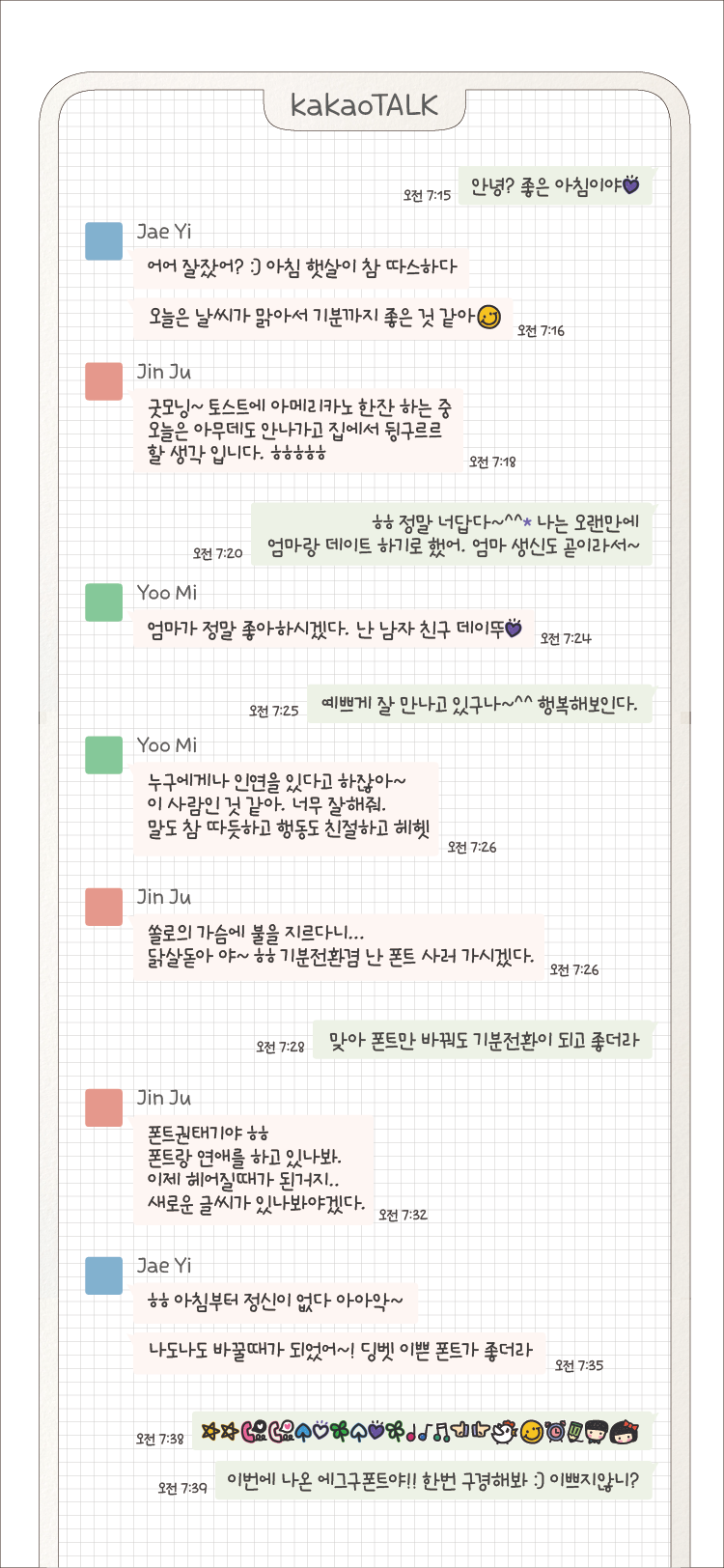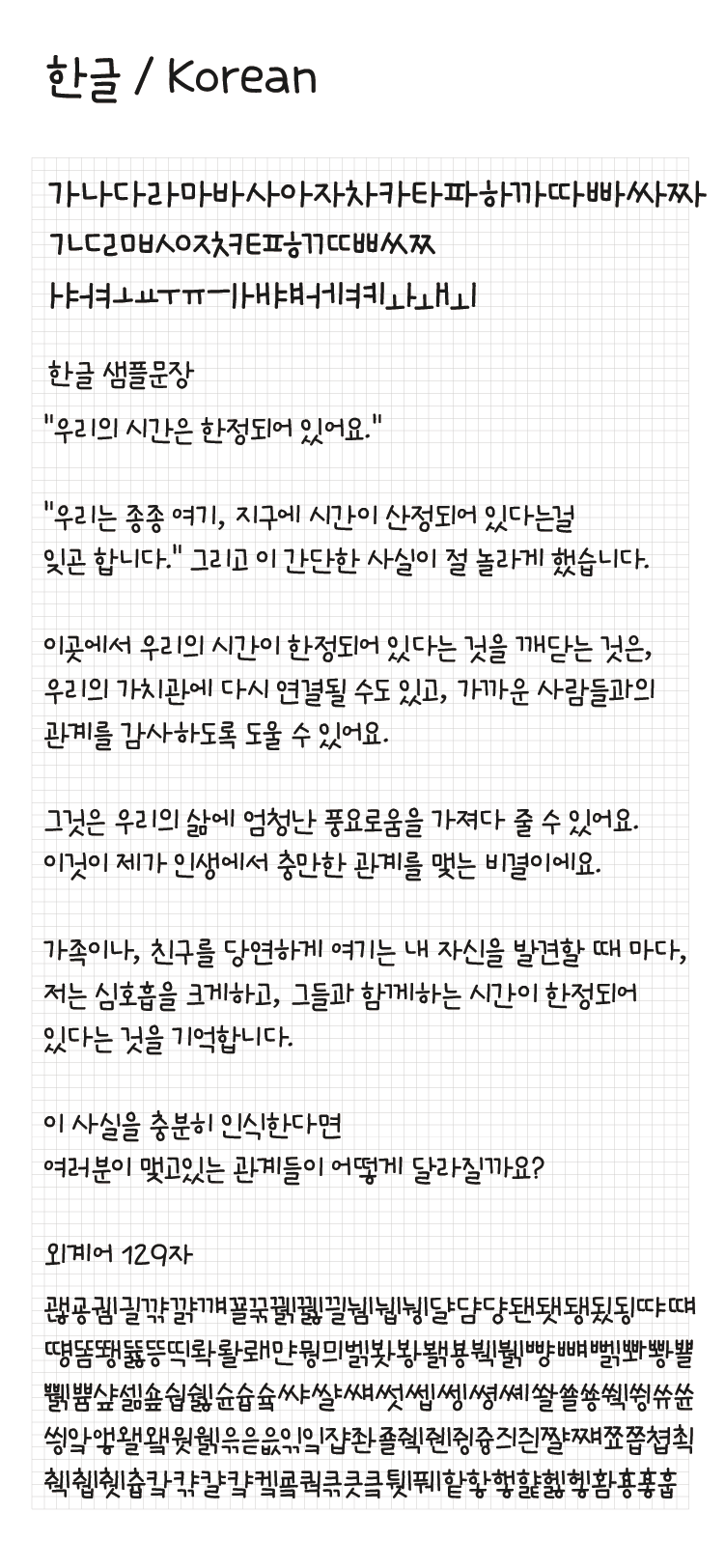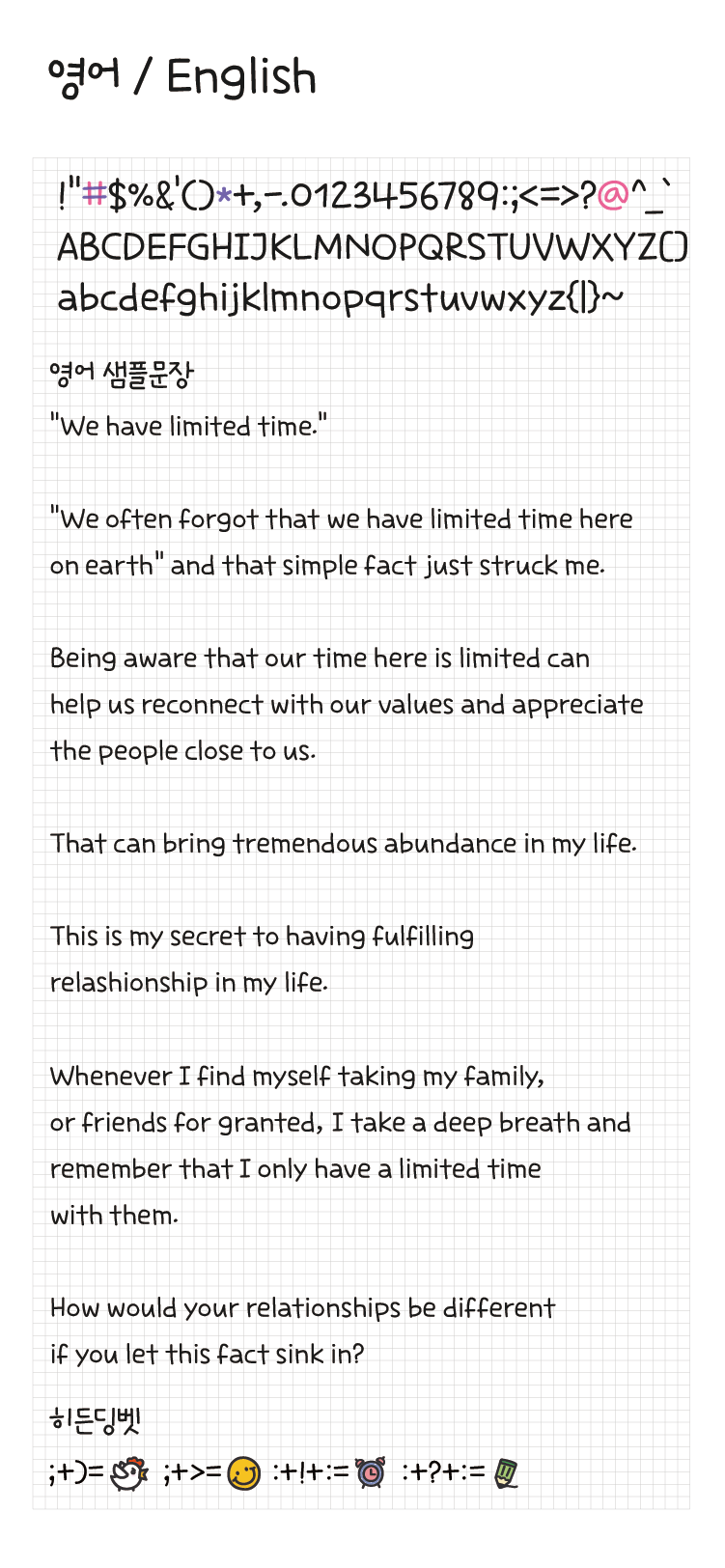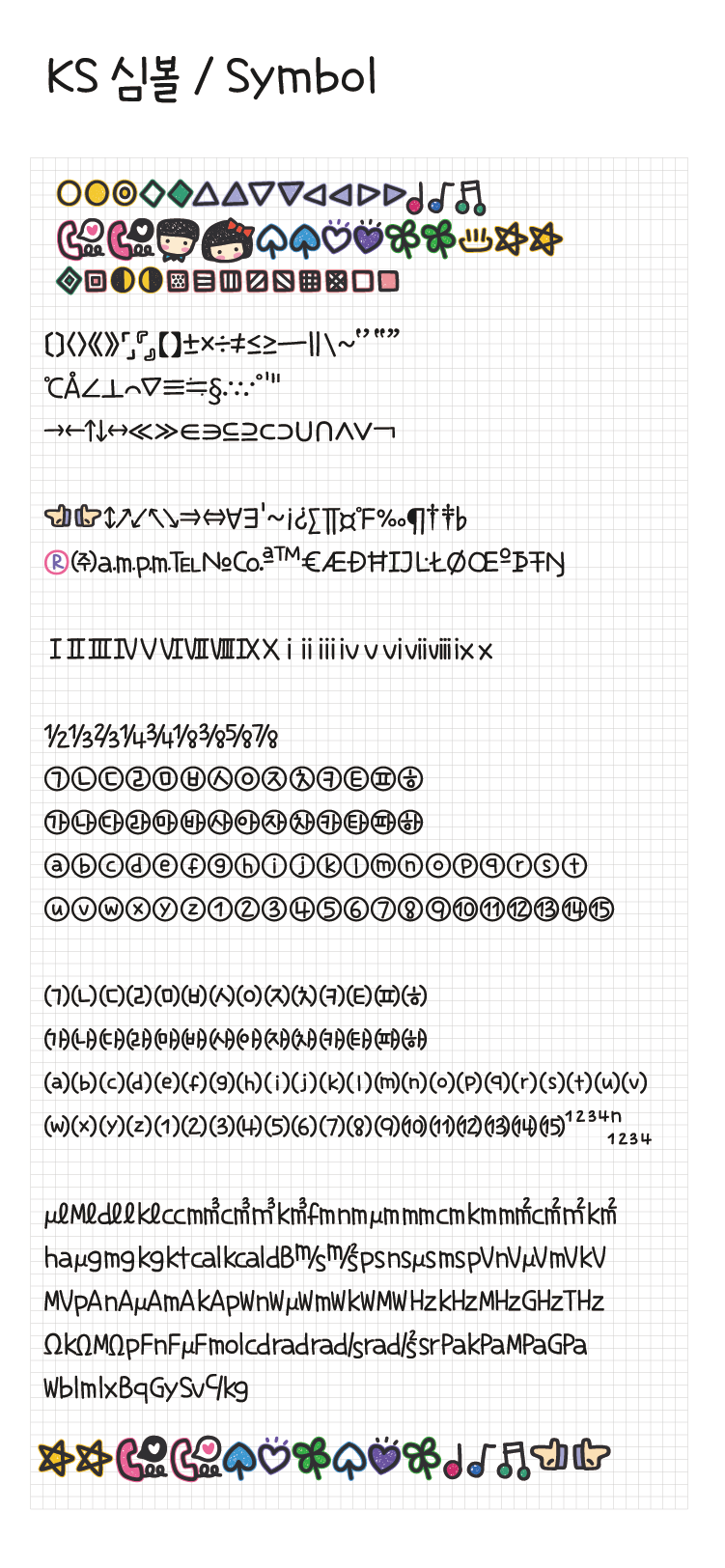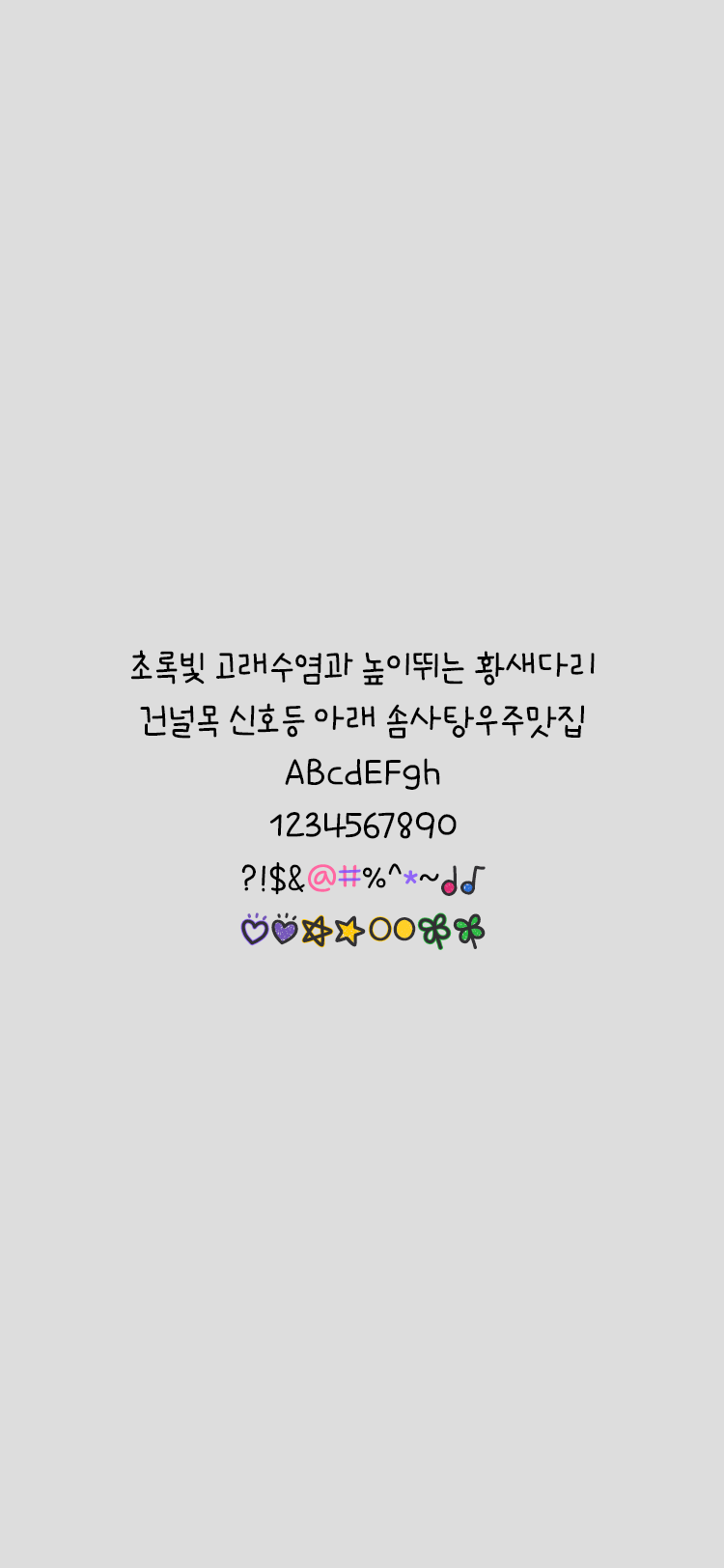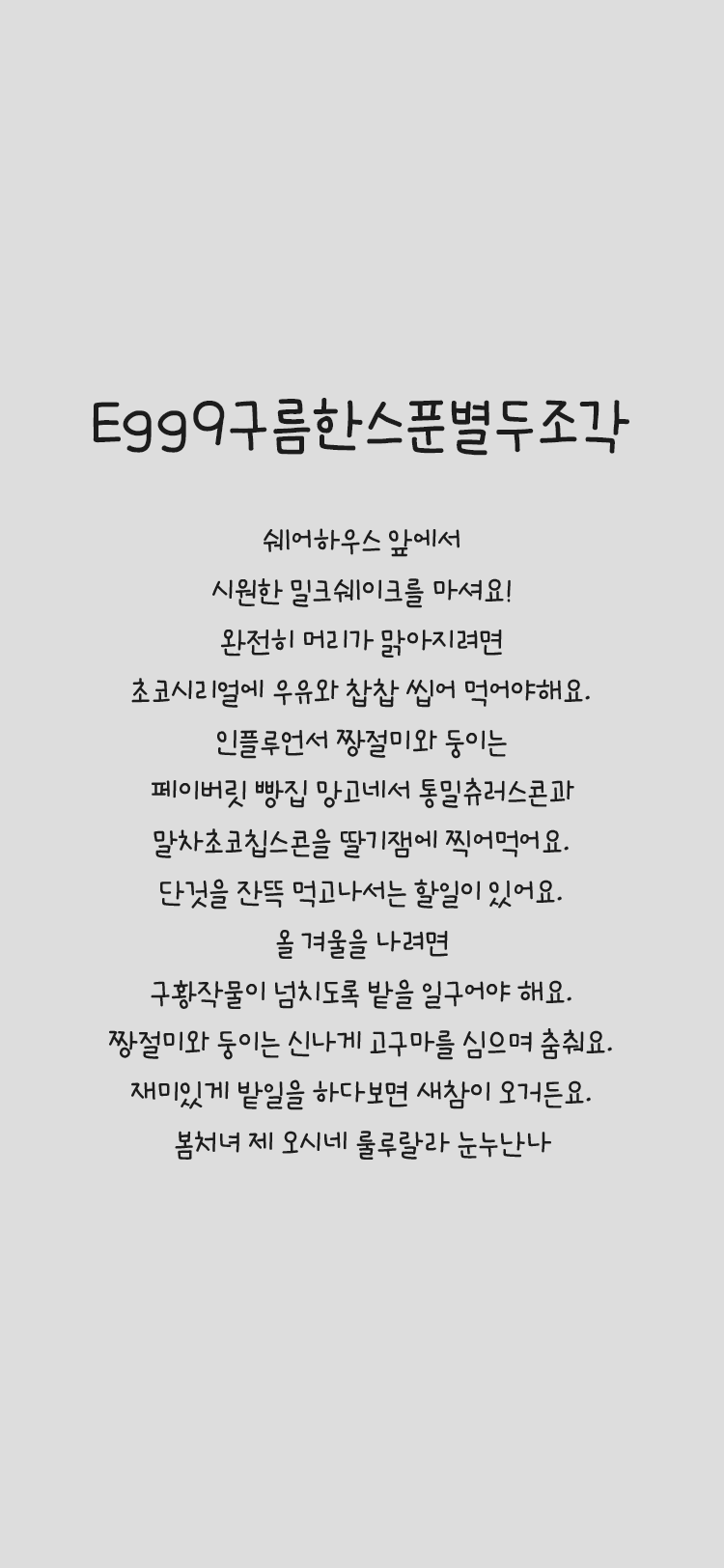
Egg9 구름한스푼별두조각
아기자기한 손글씨 스타일입니다. 히든딩벳의 경우 ;> ;) :!: :?: 입력하시면 나옵니다.
이 글꼴은 색상을 지원하지만 일부 앱에서는 작동하지 않을 수 있습니다.
• 한선주
• Egg9 구름한스푼별두조각 / Egg9 1Cloud2Stars